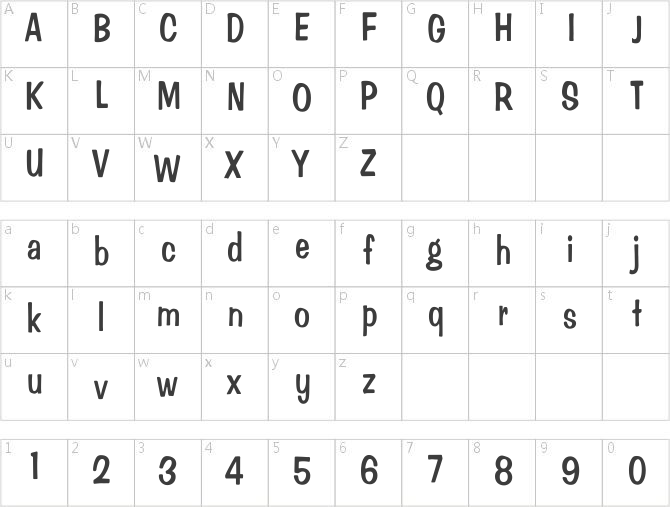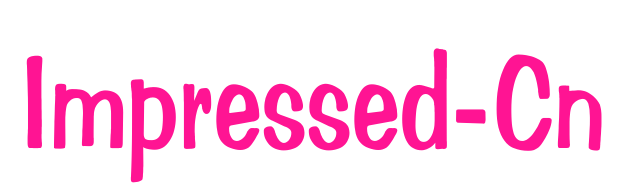
Impressed-Cn 詳情頁(yè)
Impressed-Cn字體字庫(kù)是一款讓人賞心悅目、百看不厭的英文字體,適合各類(lèi)廣告和產(chǎn)品包裝設(shè)計(jì)應(yīng)用,字體大小0.16MB,格式為ttf字體,上傳用戶(hù)是志誠(chéng)設(shè)計(jì),作者/版權(quán)方為未知